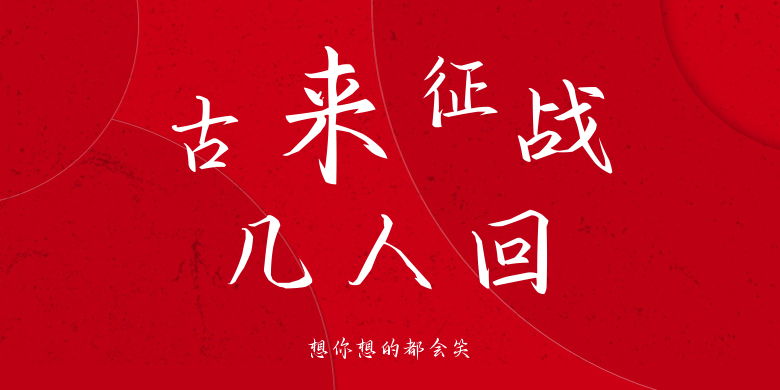
想你想的都会笑
想你想的都会笑,这款字体结构工整、笔画清晰,兼顾美观与易读性,适用于标题、正文、海报、包装、LOGO 等多种场景。字形优雅稳定,风格百搭耐看,适配日常排版与创意设计,让文字呈现更舒适、更具质感。想你想的都会笑一笔一画,皆是细节,以均衡的比例、流畅的线条打造舒适视觉体验,字形端正大气,风格简约现代。无论是商业设计、品牌宣传还是日常排版,都能轻松驾驭,让文字更有格调与力量。想你想的都会笑字体下载。